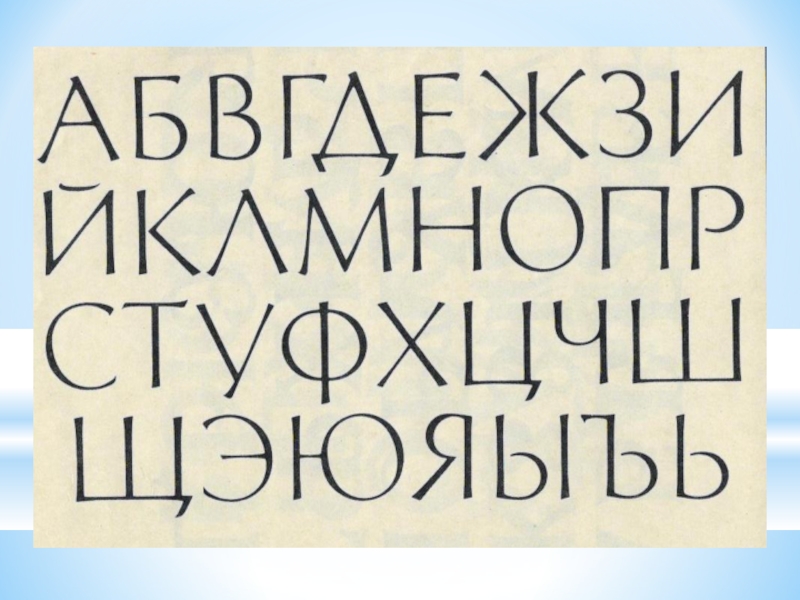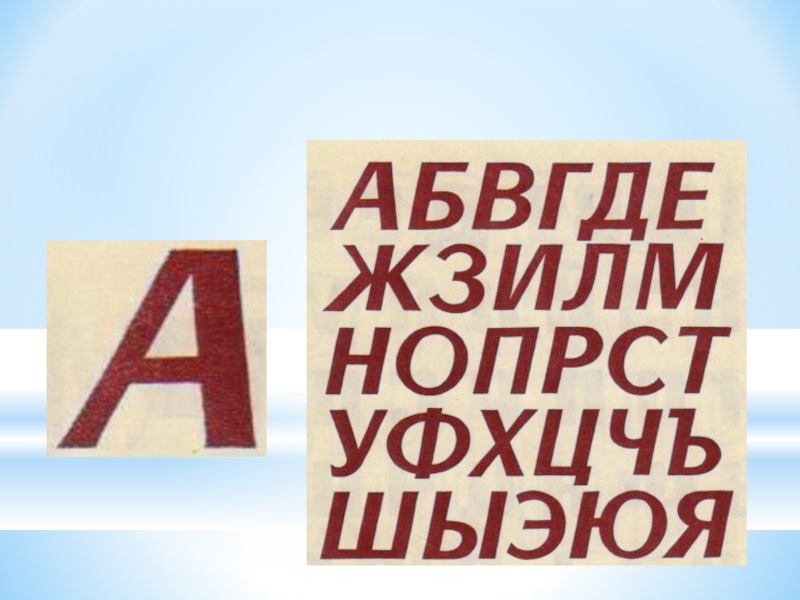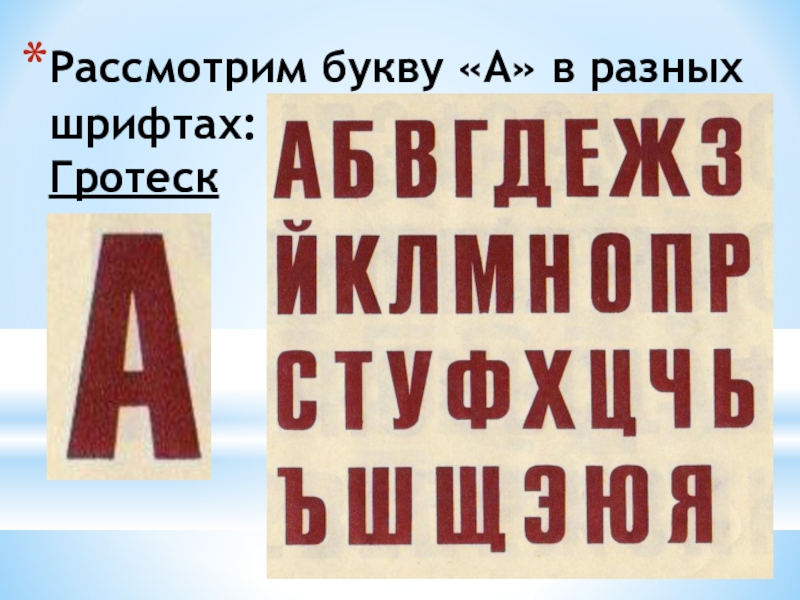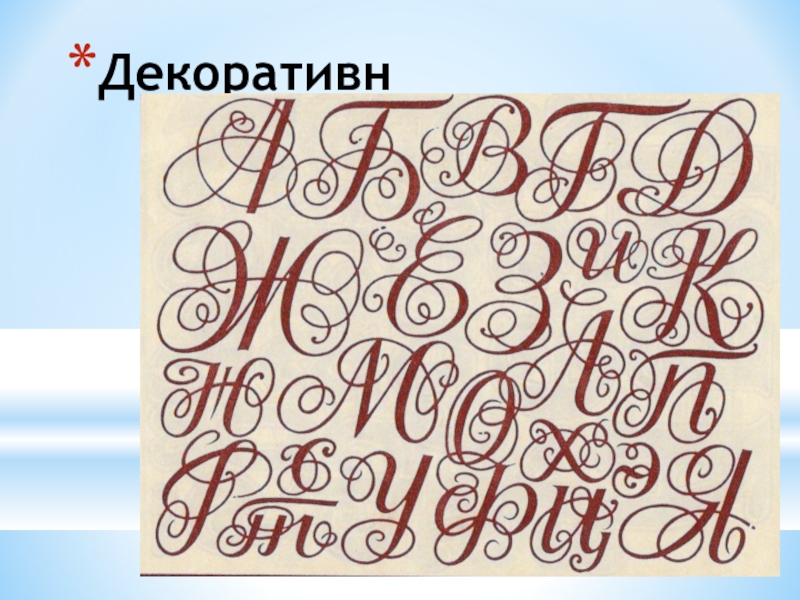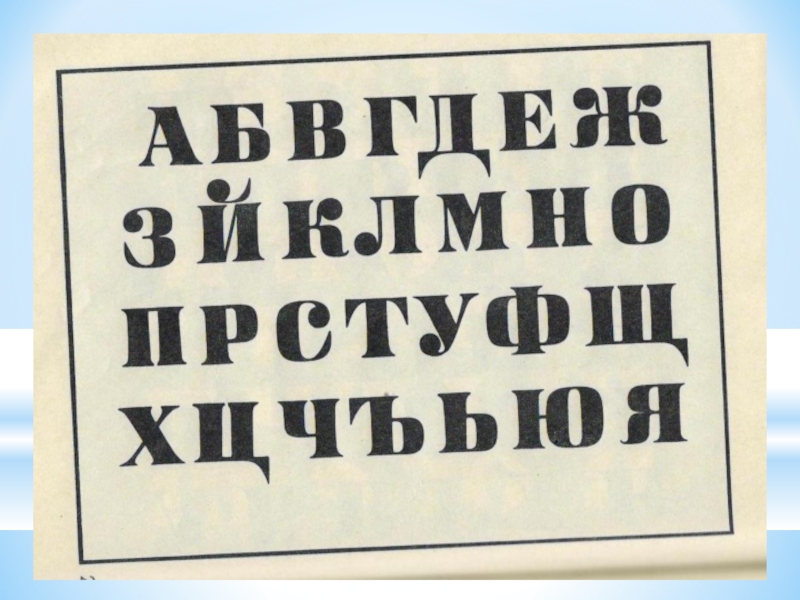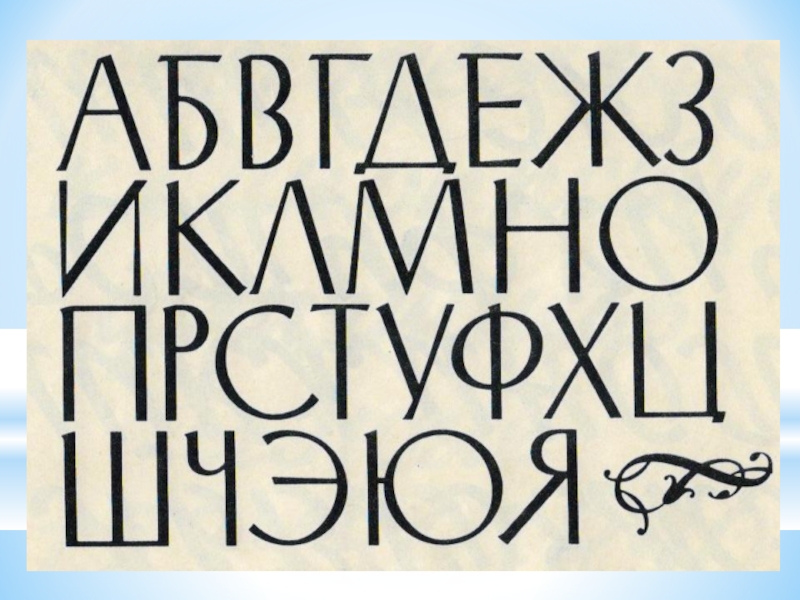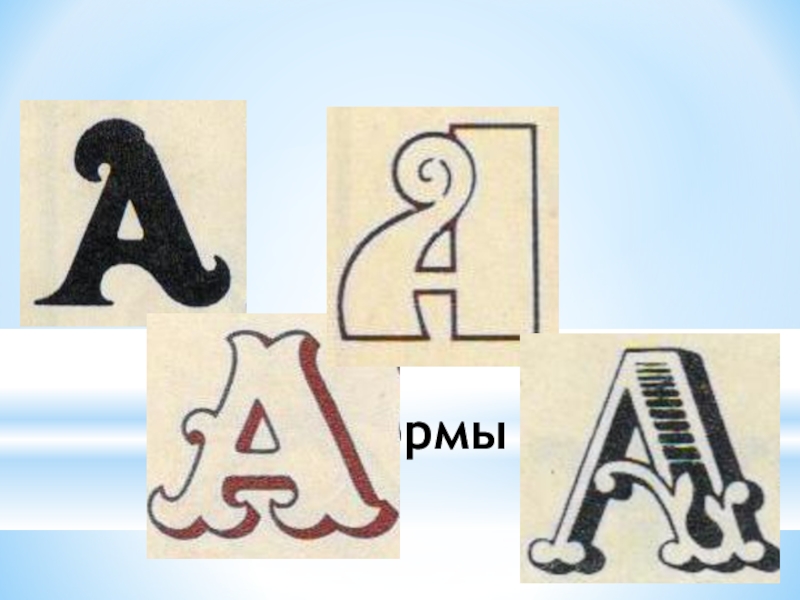
Шрифт – это буквы текста.Он бывает самый разнообразный:Большой Маленький Закруглённый Угловатый Жирный Тонкий…
Шрифт. Виды шрифтов
Изобразительное искусство 7 классШрифт.  Виды шрифтов
Слайд 2Шрифт – это буквы текста.
Он бывает самый разнообразный:
Большой
Маленький Закруглённый Угловатый
Жирный Тонкий…
Шрифт – это буквы текста.Он бывает самый разнообразный:Большой    Маленький
Слайд 8Элементы буквы
Основной элемент
Соединительный элемент
Засечка
Элементы буквыОсновной элементСоединительный элементЗасечка
Слайд 9Рассмотрим букву «А» в разных шрифтах: Гротеск
Рассмотрим букву «А» в разных шрифтах: Гротеск
Слайд 10Египетский
Египетский
Слайд 11Стандартный чертёжный
Стандартный чертёжный
Слайд 12Ленточная антиква
Новая антиква
Трафаретный
Рукописный курсив лента
Ленточная антикваНовая антикваТрафаретныйРукописный курсив лента
Слайд 13Декоративный
Декоративный
Слайд 14Формы засечки
Формы засечки